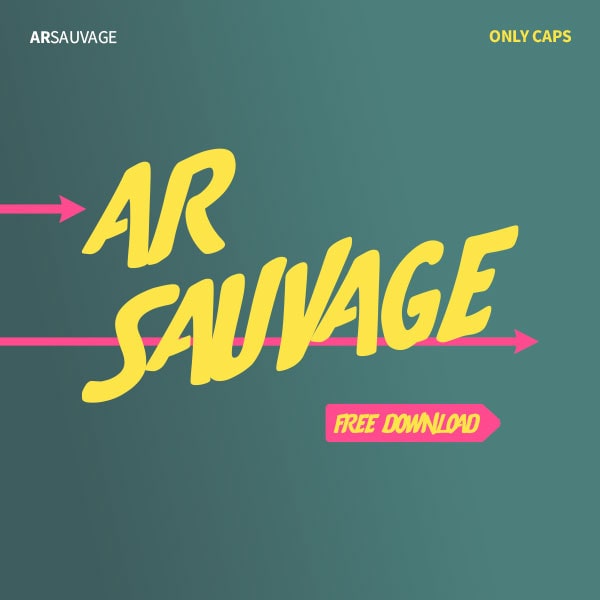
Font Ar Sauvage découvrez la majesté de la nature avec Font Ar Sauvage, une police d’écriture captivante qui incarne l’esprit de l’aventure et de la découverte. Inspirée des paysages sauvages, cette police unique ajoutera une touche d’authenticité à vos créations.
Un style rustique et élégant
Font Ar Sauvage dégage un charme rustique tout en conservant une élégance intemporelle. Chaque lettre est soigneusement conçue pour refléter la beauté brute de la nature, faisant de cette police un choix parfait pour les projets qui nécessitent à la fois robustesse et raffinement.
Polyvalence : Des possibilités infinies
Avec une gamme de caractère capitale, Font Ar Sauvage vous offre une polyvalence inégalée. Que vous souhaitiez concevoir des logos accrocheurs, des bannières percutantes ou des invitations à l’aventure, cette police s’adaptera parfaitement à toutes vos idées créatives.
Polyvalence : Des possibilités infinies
Avec une gamme de caractère capitale, Font Ar Sauvage vous offre une polyvalence inégalée. Que vous souhaitiez concevoir des logos accrocheurs, des bannières percutantes ou des invitations à l’aventure, cette police s’adaptera parfaitement à toutes vos idées créatives.
Font AR Sauvage : L’éléfance audacieuse pour votre logo et branding
La Font Ar Sauvage est un choix de premier ordre pour la création de logo et branding. Avec son mélange unique de rusticité et d’élégance, cette typographie apportera une identité inoubliable à votre marque. Que vous dirigiez une entreprise d’aventure en plein air ou une marque qui valorise l’exploration, la Font Ar Sauvage saura incarner l’esprit intrépide de votre entreprise. Grâce à ses lignes audacieuses et ses détails raffinés, cette police donnera à votre logo une aura distincte et professionnelle. Faites forte impression sur votre public cible en optant pour la Font Ar Sauvage dans votre stratégie de branding, et démarquez-vous avec une typographie qui évoque l’appel de l’aventure.
Une typographie en lettres capitales
La Font Ar Sauvage se distingue par sa majestueuse présence en lettres capitales. Chaque caractère est soigneusement dessiné pour capturer l’essence même de l’aventure et de la nature sauvage. Cette typographie en majuscules offre une lisibilité saisissante, parfaite pour attirer l’attention sur vos créations. Que vous souhaitiez créer des titres percutants, des logos impactants ou des messages inspirants, la Font Ar Sauvage vous offre une flexibilité inégalée. Laissez libre cours à votre créativité et ajoutez une touche audacieuse à vos projets avec cette typographie captivante en lettres capitales. Que votre imagination s’envole vers de nouveaux horizons avec la Font Ar Sauvage !
La typographie AR Sauvage une conception professionnelle
Notre police est le fruit d’une conception professionnelle et d’un travail méticuleux. Chaque détail est pris en compte pour vous offrir une expérience typographique exceptionnelle, que vous soyez un designer chevronné ou un débutant passionné.